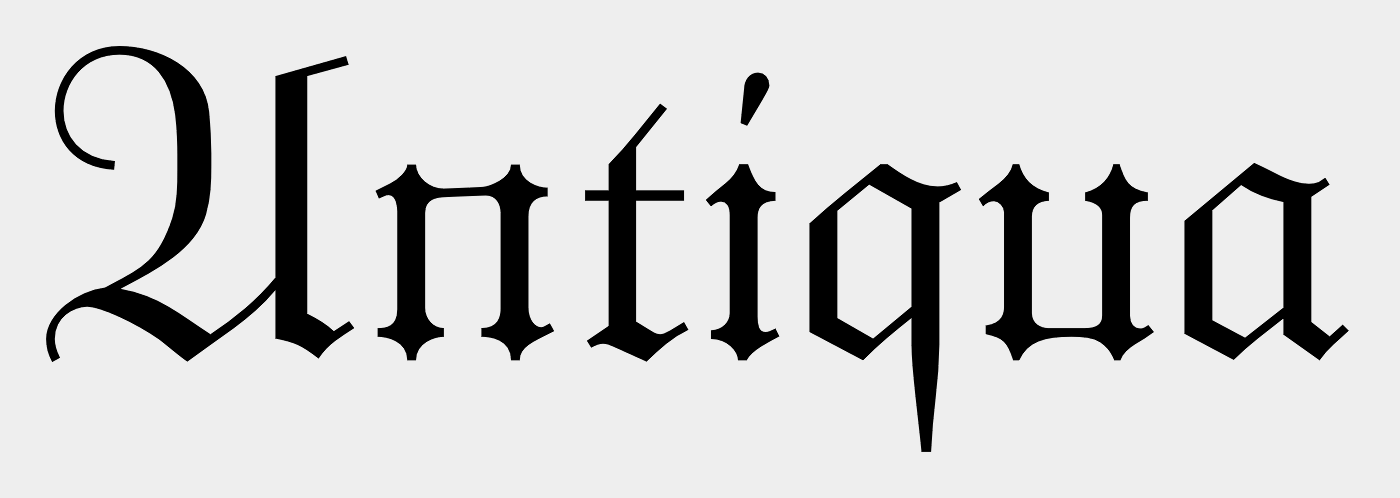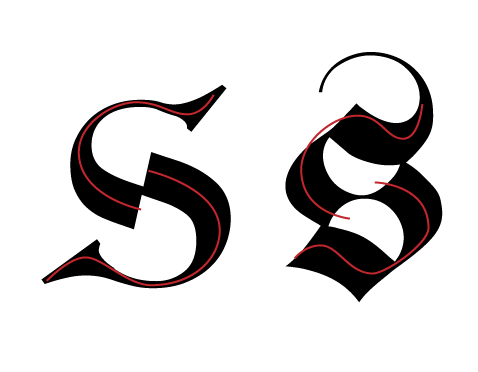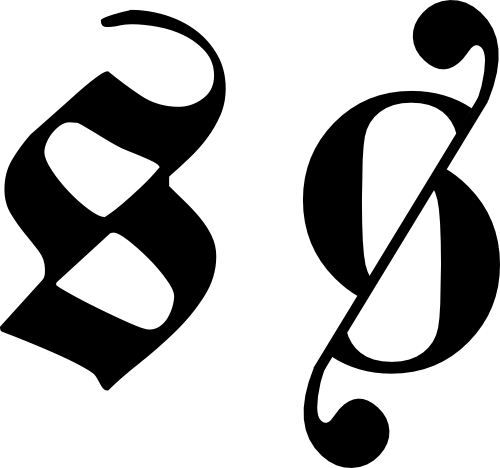
"Antiquaisierte" Fraktur - Gibt's das?
Ich weiß nicht, ob ich mit dieser Frage hier in diesem Themenbereich richtig bin, aber ansonsten kann man sie schwer zuordnen.
Mich hat vor einiger Zeit ein Freund, der sich sehr für alte Sprachen und Schriften interessiert und auch selbst gern Experimente damit betreibt, gefragt, ob es wohl eine Schrift gäbe, die zwar vom Erscheinungsbild her eine Antiqua ist, sich aber die Grundgerüste von Fraktur-Lettern "einverleibt" hat.
Also, man stelle sich folgendes Szenario vor: Ein Paläograph/Philologe, der sich zufällig auch mit Schriftgestaltung beschäftigt, findet ein Fraktur-Alphabet, erkennt aber aus irgendeinem Grund nicht, dass es sich im Grunde um die selben Buchstaben handelt wie in der Antiqua. Natürlich muss er annehmen, es handle sich um ein selbstständiges Schriftsystem. Nun will er eine Abhandlung darüber herausgeben und fängt dabei an, die eigenartigen Frakturformen dem Duktus der Antiqua anzupassen.
So oder so ähnlich ist es ja auch bei der Kyrilliza passiert, wenn ich recht informiert bin.
Also, lange Rede, kurzer Sinn: Kennt jemand von euch so eine Schrift? Im Prinzip so etwas wie bei der Andron (Alternativset DEU http://www.signographie.de/cms/front_content.php?idart=310), nur konsequenter umgesetzt.
Das würde ja im Prinzip zum größten Teil nur bei den Versalien Auswirkungen haben. Ich bin in Gedanken eben mal die Gemeinen durchgegangen und ein o gebrochen oder in Antiqua ist nunmal ein Kreis – da macht nur der Duktus den Unterschied.
Umgekehrt gilt ja die Leibziger Antiqua als Beispiel einer gebrochenen Antiqua ...
Ich hab mal schnell aus Teilen einer Bodoni das zusammengezimmert, was ich meine:
Die Proclamate links ist leider kein sehr gutes Beispiel, aber ich hab leider keine bessere Fraktur.
Also man sieht, dass das s hier ja so aufgebaut ist, dass zwei punktsymmetrische und versetzte Bögen mit einer Diagonale geteilt werden, an deren Ende (bzw. manchmal auch an beiden) ein Schweif ist.
Unser typophiler Philologe hat nun genau diese Formen in eine (klassizistische) Antiqua zu übertragen versucht.
Stimmt, oft käme tatsächlich dasselbe Ergebnis raus wie bei einer normalen Antiqua (eben z.B. beim o). Aber es gibt ja durchaus viele Buchstaben in gebrochenen Schriften, die völlig anders "konstruiert" werden, z.B. k, x, y.
Kommt natürlich auch immer auf die gebrochene Schrift an, die man gerade betrachtet ...
Ode & Co. sind nicht das, was ich suche, die versuchen ja, im Gegenteil, gebrochene Elemente (aber eben nicht das "Gerüst") in etabliertere Schriftgattungen einzuführen.
Jucken würd's mich schon, aber bei einer so - hm, technischen, wissenschaftlichen - Herangehensweise hätte ich eben gerne gewusst, ob es sowas schon gibt und wenn ja, wie der betreffende Gestalter vorgegangen ist. Wie gesagt, einen Ansatz dazu sehe ich ja schon in der Andron.
Die Diagonale, die du da zeichnest gibt es aber gar nicht. Die entsteht eher zufällig™.
Es würde wohl eher sowas bei ’rauskommen:
Didot ./. Fette Fraktur
@Lukas: Das Thema würde mich sehr interessieren! Allerdings liegt mein Interesse abseits der Wissenschaftlichkeit und eher beim Formalen: Ich finde Dein Beispiel ausgesprochen dekorativ und könnte mir vorstellen, dass sich im Layoutbereich damit sehr schön spielen ließe.
@Kathrin: Ja, finde ich auch. Aber es ist eben auch der "Gag", der mich reizt (und der meinen Freund sicher auch auf diese Idee gebracht hat).
@Schnitzel: Wie gesagt, die Proclamate war ein schlechtes Beispiel. Besser wäre Dürers Textura (http://cdn.ilovetypography.com/img/2010/08/duerer_textualis_constr_02.jpg), da sieht man ganz deutlich die eingezeichnete Diagonale. Ja, ich weiß, ich habe "Fraktur" geschrieben, vielleicht hätte ich besser auf "gebrochene Schriften" verallgemeinern sollen ...
Aber deine Variante mit der Didot ist auch ganz reizvoll!
Die Centralschrift von C. G. Schoppe geht ein wenig in diese Richtung. Dort wurden Antiqua- mit Frakturelementen vermischt. Weitere Informationen und Bilder gibt es auf der Website http://vau-ef-be.beepworld.de/weiteres.htm
Es gibt auch eine Digitalisierung dieser Schrift unter dem Namen Kombine: http://haroldsfonts.com/portfolio/kombine/
Eine Schrift, bei der konsequent die typischen Frakturformen beibehalten und dem Antiqua-Duktus angepasst wurden, wie du es beschreibst, gibt es meines Wissens nicht. Als weitere Inspirationsquelle vielleicht dieser Schriftzug (ist allerdings eine Sans): http://www.typejockeys.at/projects/Werbezimmer
Mich treibt seit längerem die Frage um, wie die Fraktur sich hätte weiterentwickeln können und ich arbeite auch schon seit einiger Zeit an einer Sans-Serif-Schrift, der ein ähnlicher Gedanke zugrunde liegt. Als Hobby-Schriftgestalter fällt mir die Umsetzung aber nicht leicht.
@boernie: Naja, nur weil Zapf das gesagt hat, heißt es ja nicht, dass es nicht doch anders gekommen sein könnte ... ;-)
Aber wahrscheinlich hat er schon irgendwie recht, nehme ich an ... Aber wer weiß schon, was die Zukunft bringt?
@j4y: Ja, ganz genau so hab ich mir das vorgestellt, Vielen Dank! Jetzt kann man natürlich hergehen und je nach der Fraktur, die man betrachtet, auch ein großes R als Grundlage nehmen, weil der kleine obere Balken des k in manchen Frakturschriften ja auch einen Bogen schlägt und sich wieder mit dem Stamm verbindet. - Es gäbe unzählige Möglichkeiten!